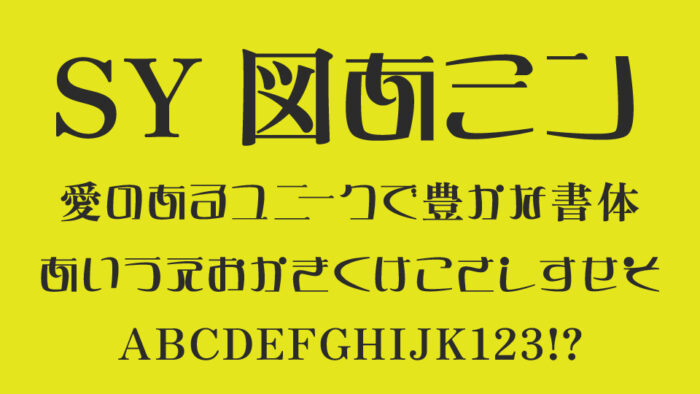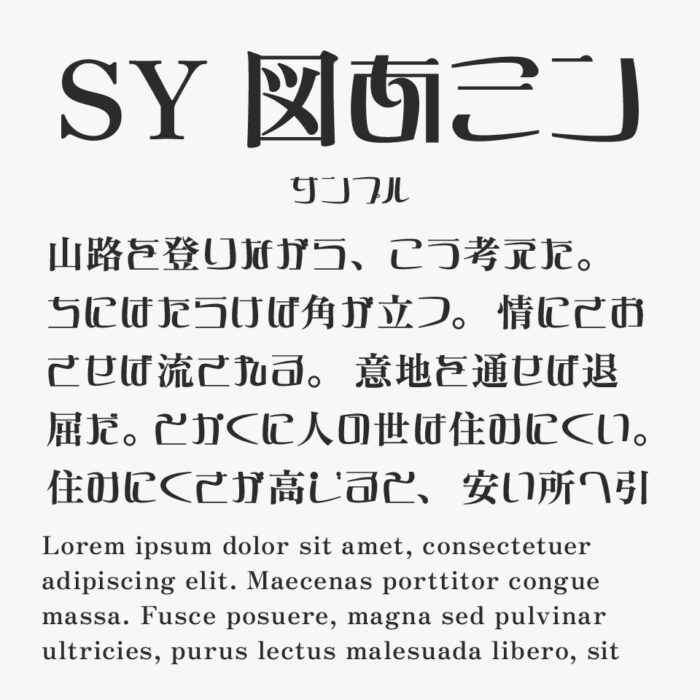
SY図あミン
SY図あミンフォントは、大正から昭和初期にデザインされた「図案文字」をヒントに制作した仮名と漢字は「ZENオールド明朝」を組み合わせ制作されたフォントです。
「図案文字」は図案家の手によって書かれたひと文字ひと文字は、大正時代のような雰囲気が表現され、どこかモダンながらレトロで遊び心を感じさせるフォントです。